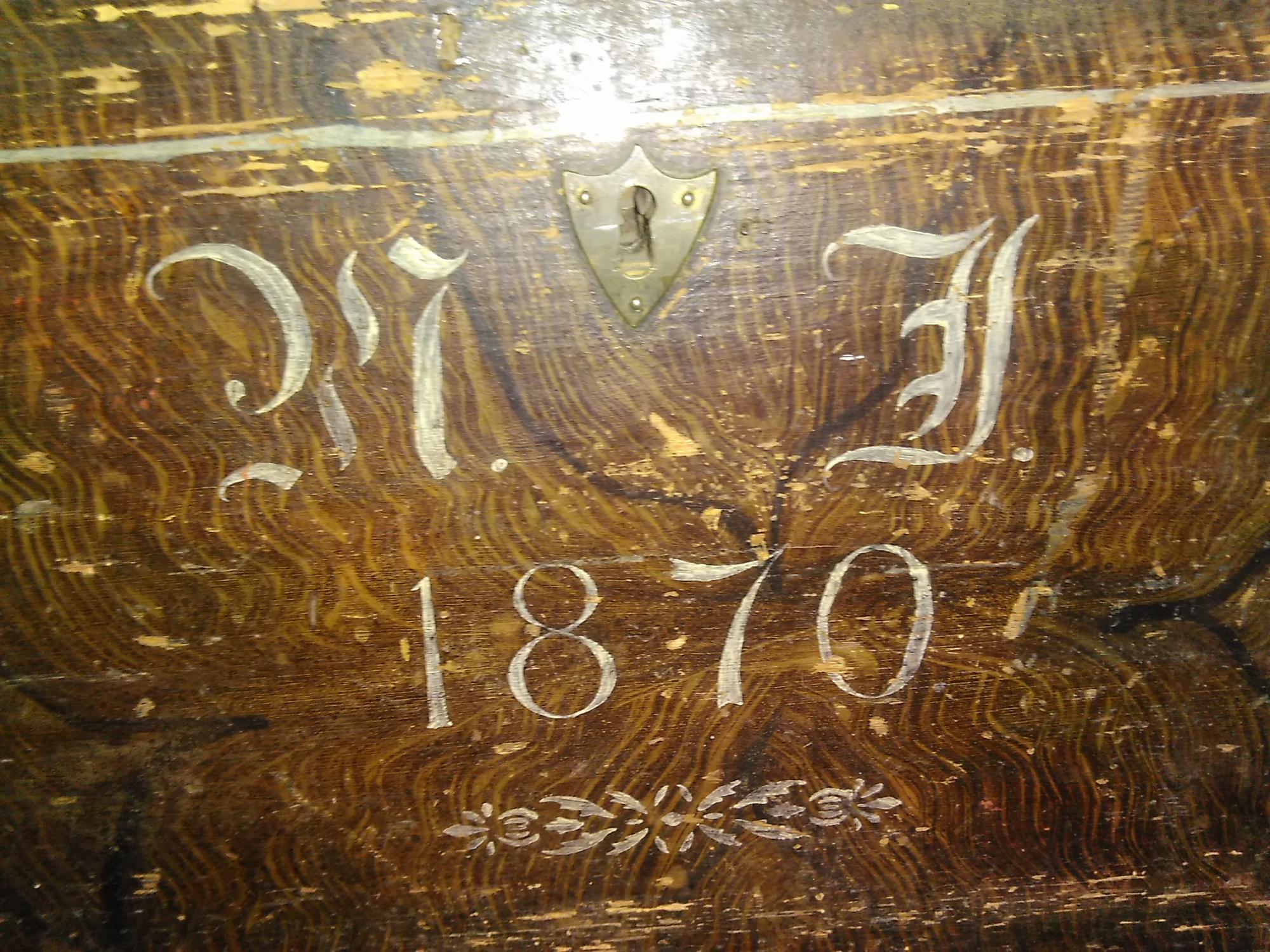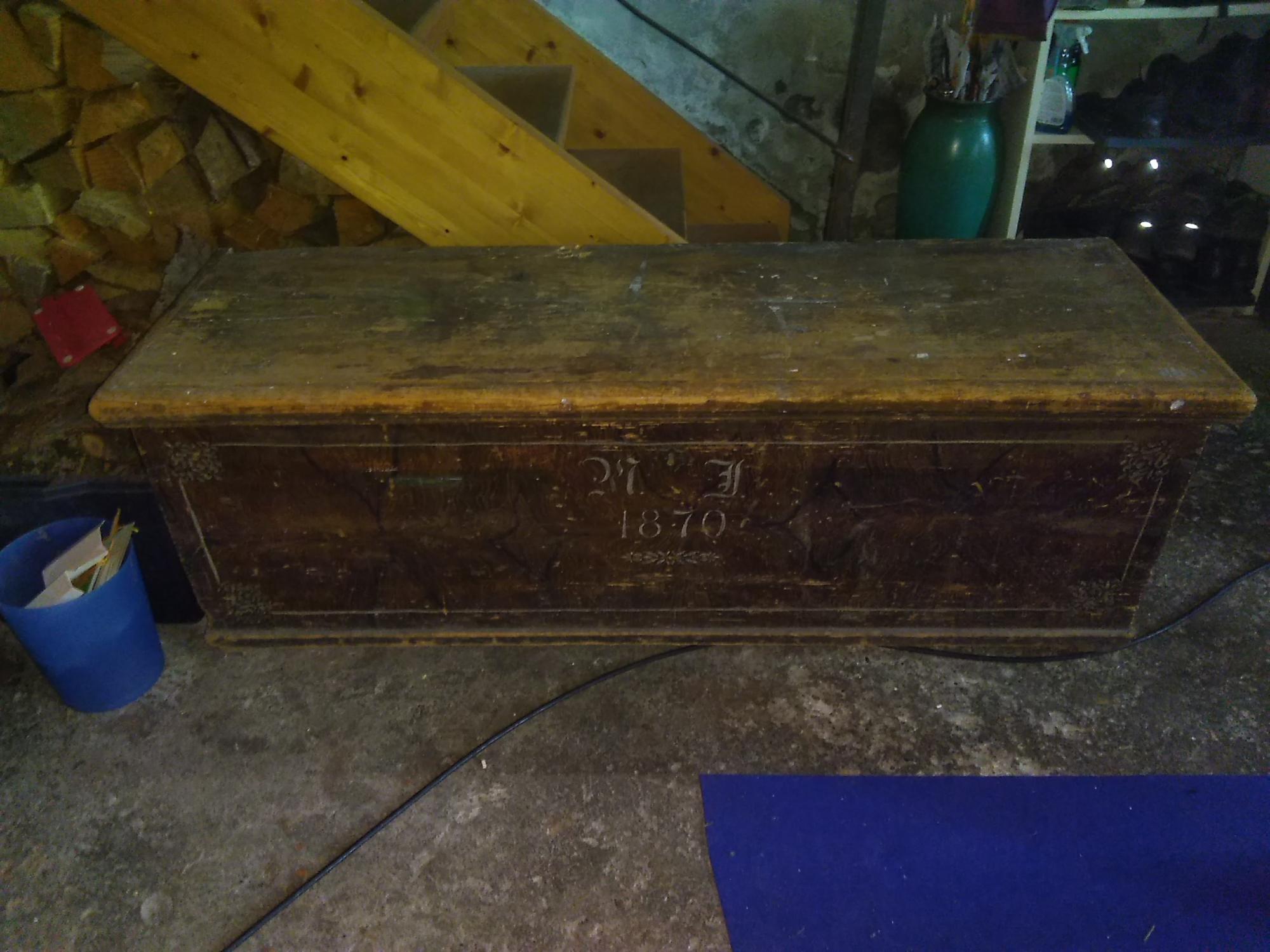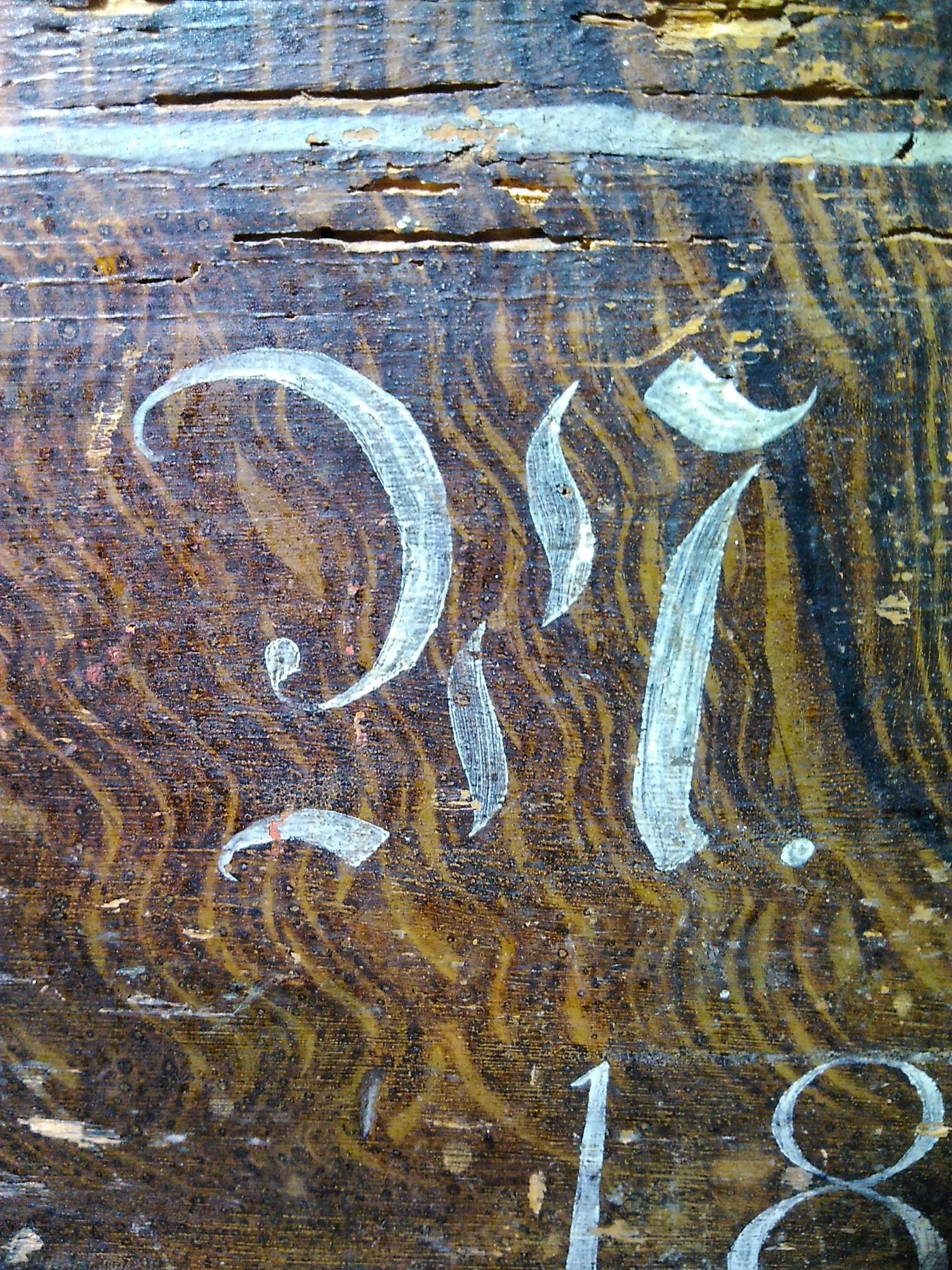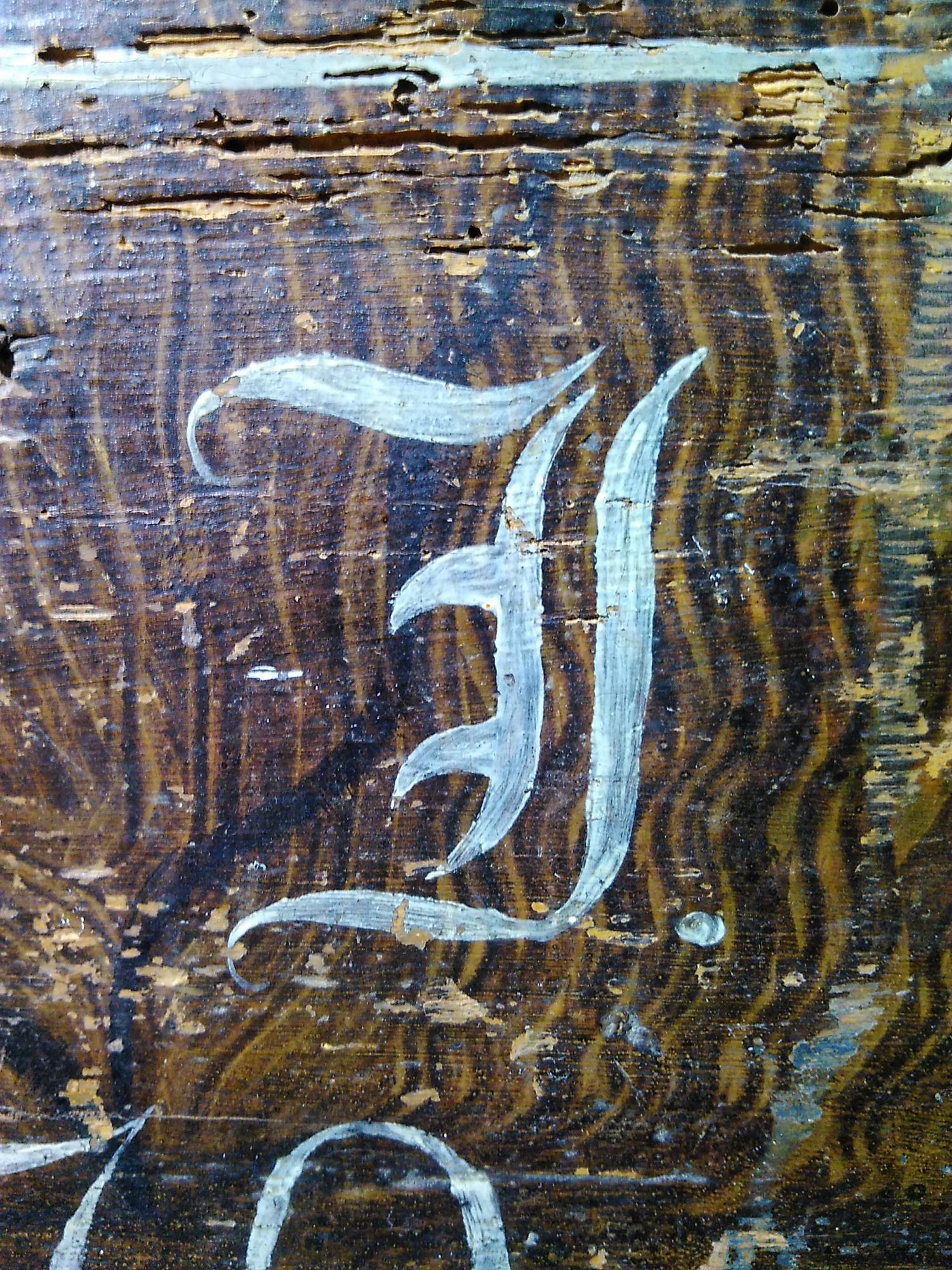
Alte Holztruhe - Schriftart und Übersetzung gesucht
Folgende Holztruhe (Möglicherweise handelt es sich um eine alte Hochzeitstruhe) stand lange Zeit bei meiner Grossmutter auf dem Dachboden.
Die Truhe stammt evtl. aus der Schweiz oder aus Österreich. Der Versuch die aufgemalten Initialen zu entziffern war leider nur von mässigem Erfolg gekrönt.
Kann mir jemand sagen ob dies eine "offizielle" Schriftart war und welche Buchstaben da aufgemalt sind?
Ich lese dort W I.
Grad nochmal nachgesehen und noch grössere Fotos gemacht. Soweit ich dies beurteilen kann, ist da nichts grösseres abgeplatzt.
Beim ersten Buchstaben hätte ich auch auf "N" oder "M" getippt, der zweite evtl. ein "J"?
Das hatte ich auch überlegt, aber ich finde kein N oder M mit dem von links oben einleitenden Bogen.
J erscheint mir nun auch eher wahrscheinlich, die Old English hat ein solches. Das I dagegen hat nur einen Sporn.
ich hab grad per Zufall bei "unifraktur-forum" einen russischen Fraktur-Schnitt gesehen... Könnte es denn sein, dass das kein Deutsch, sondern eben Russisch o. ä. ist?
Oder dass der erste Buchstabe eine Ligatur ist? Imho könnte da auch Rl oder Kt stehen...